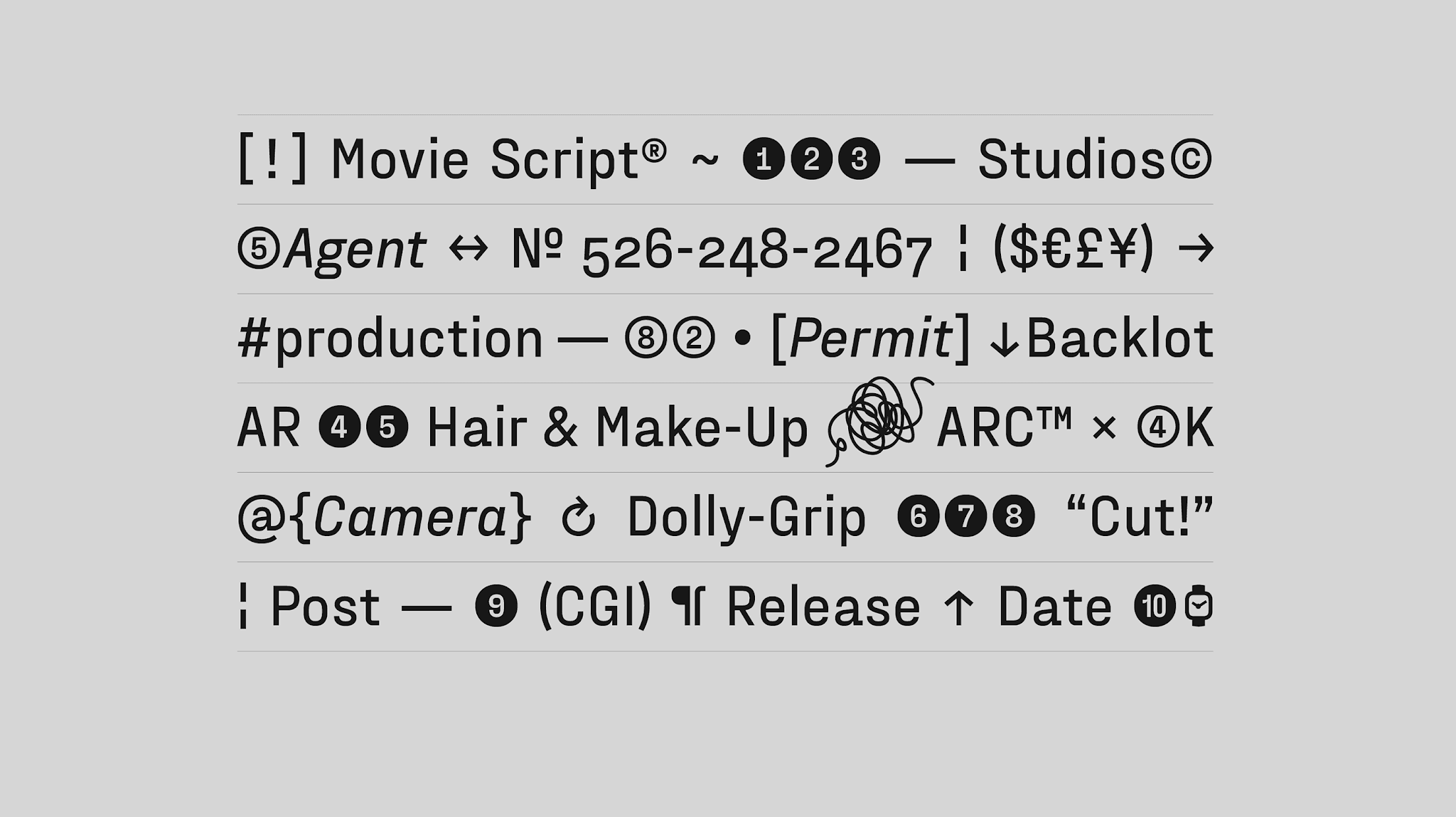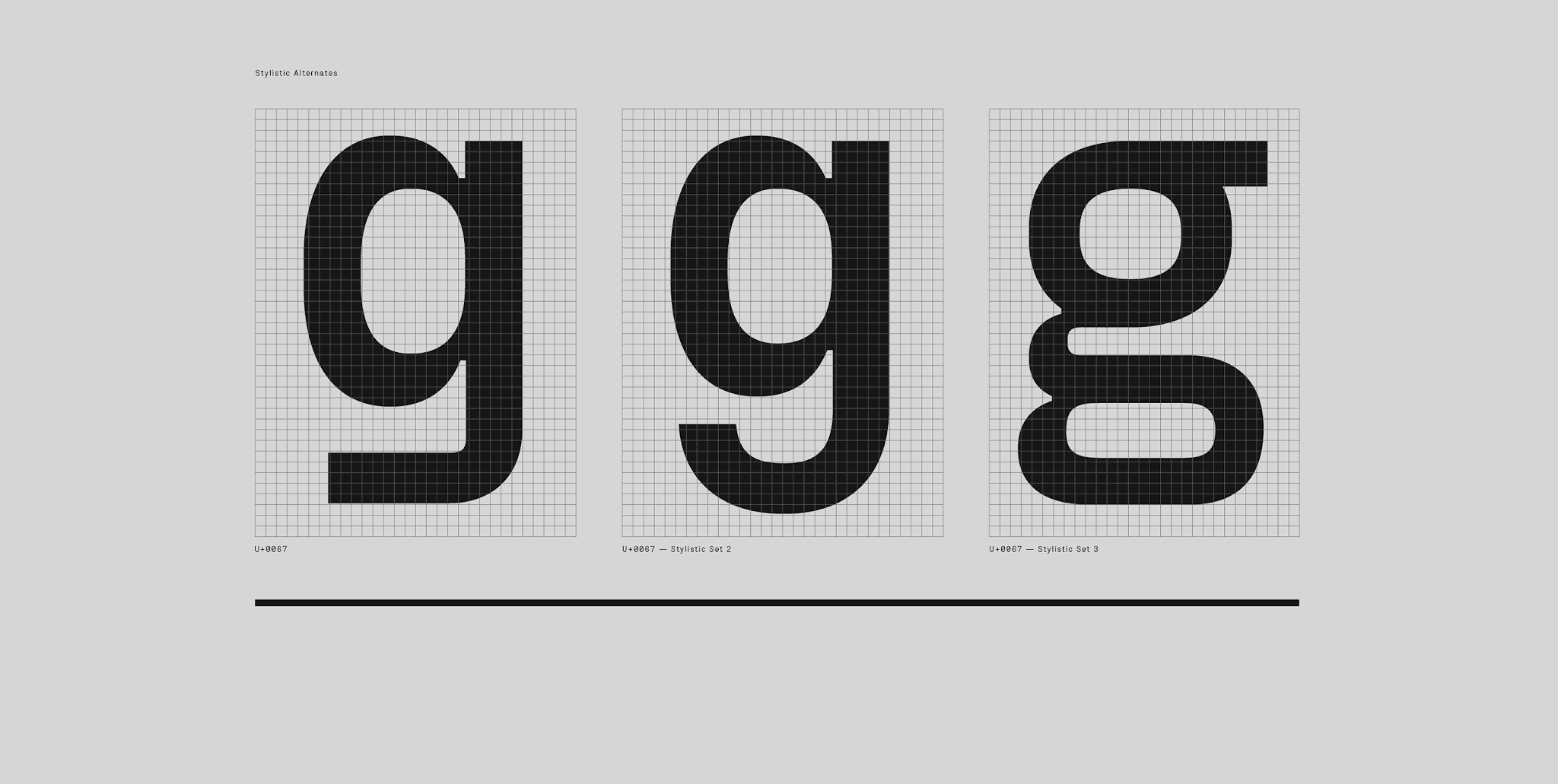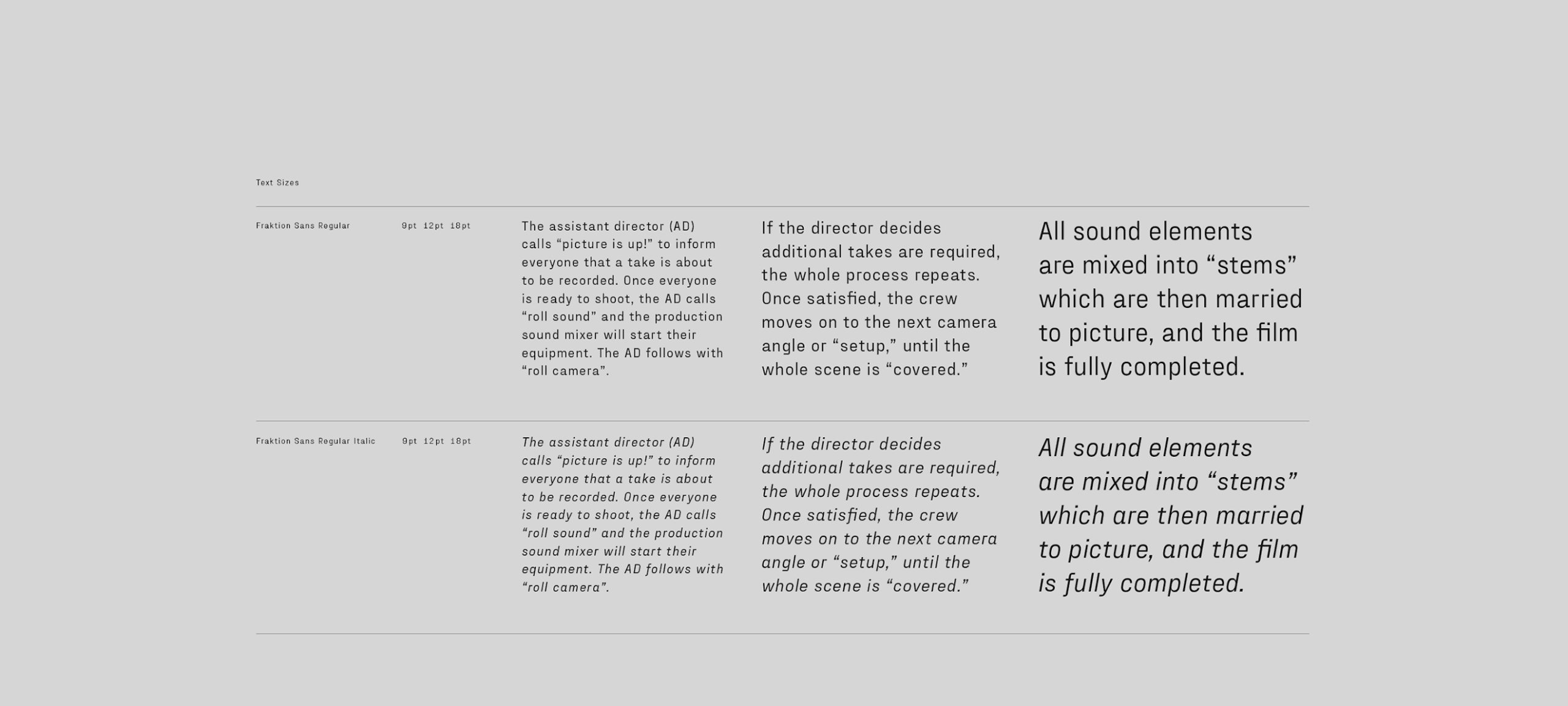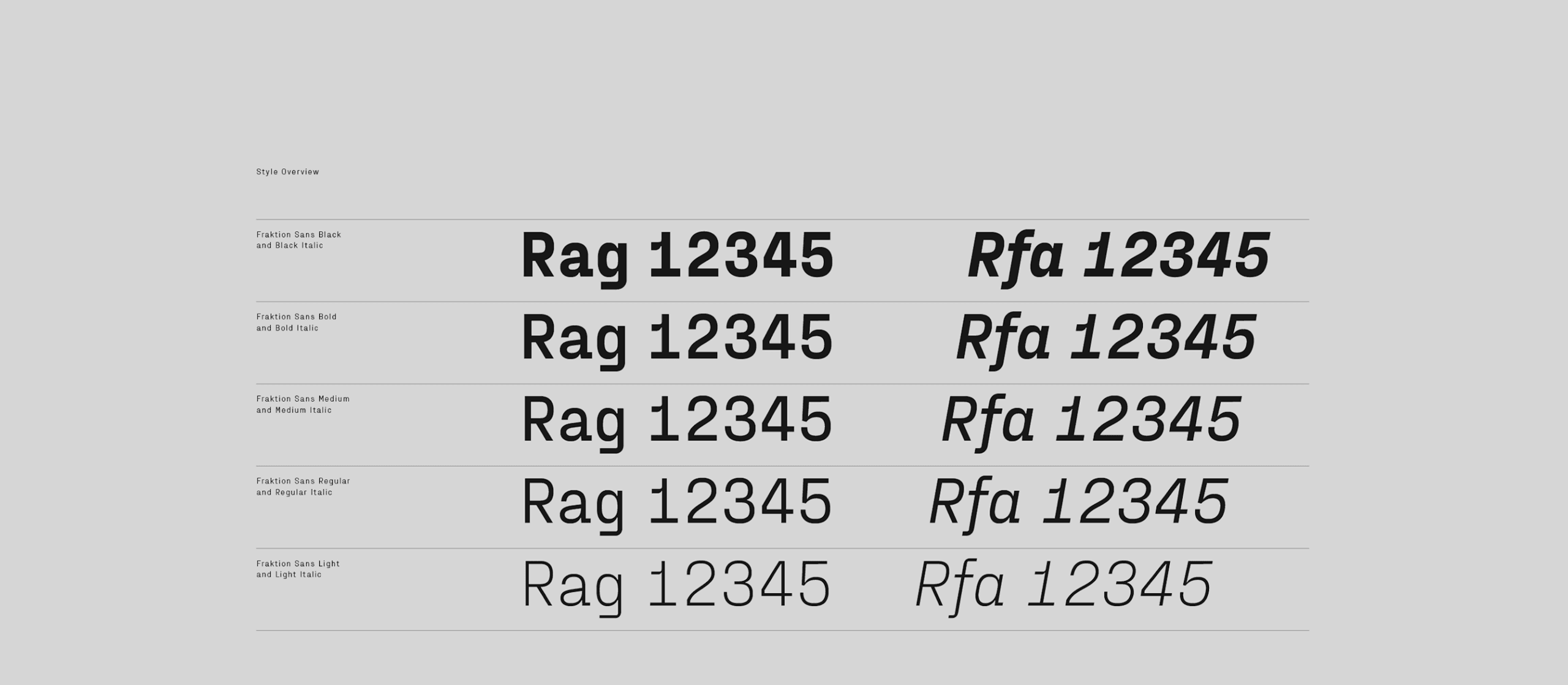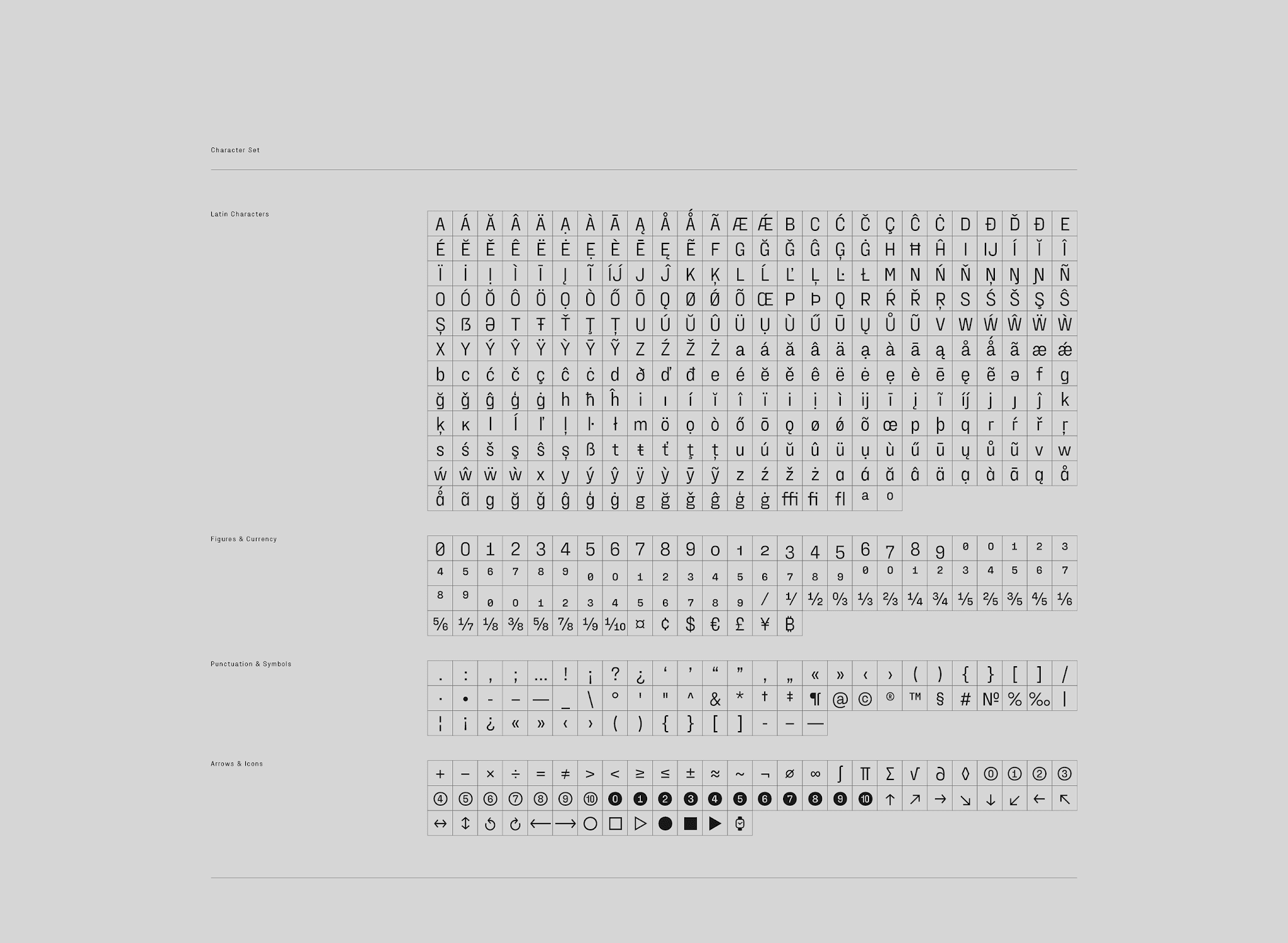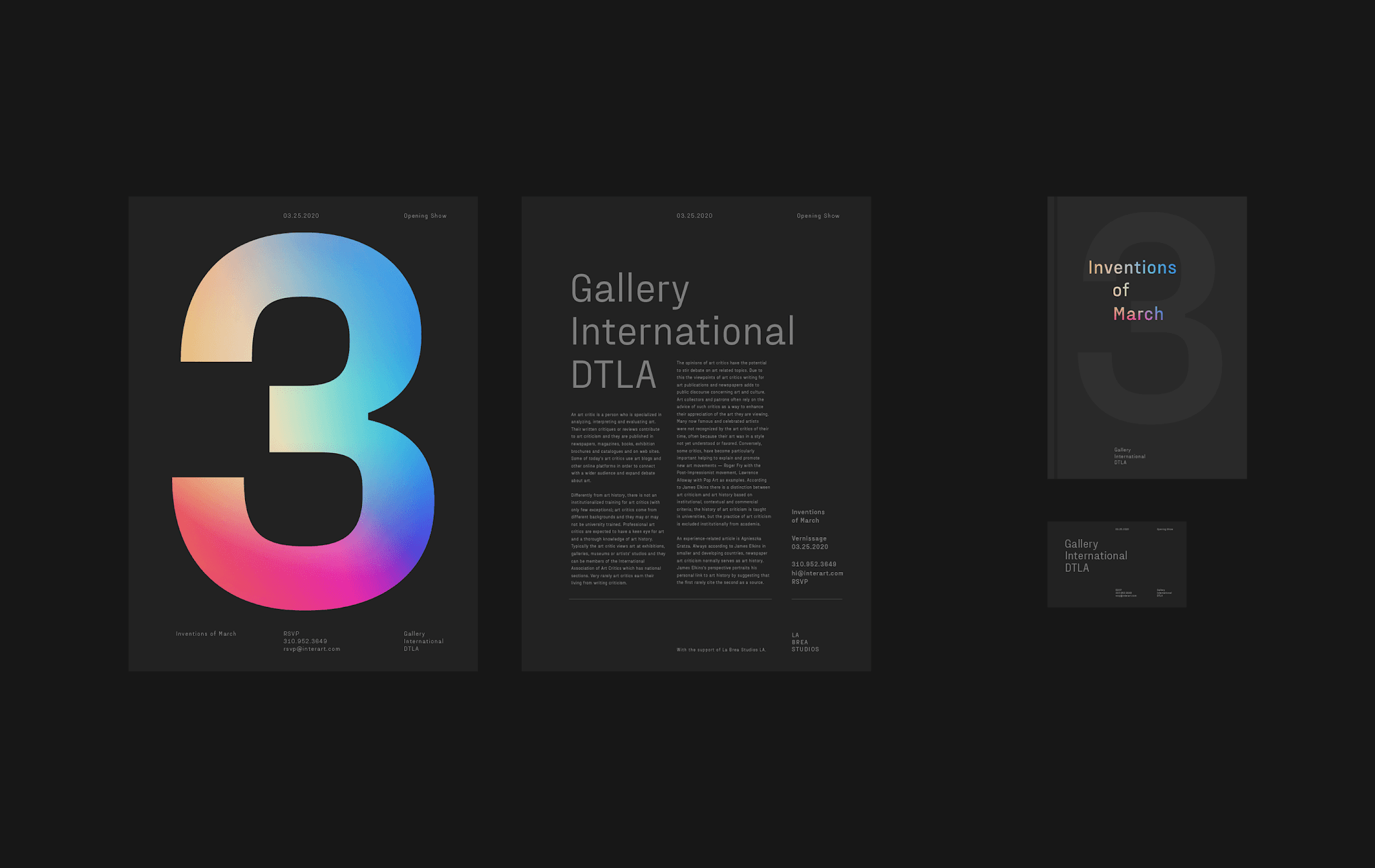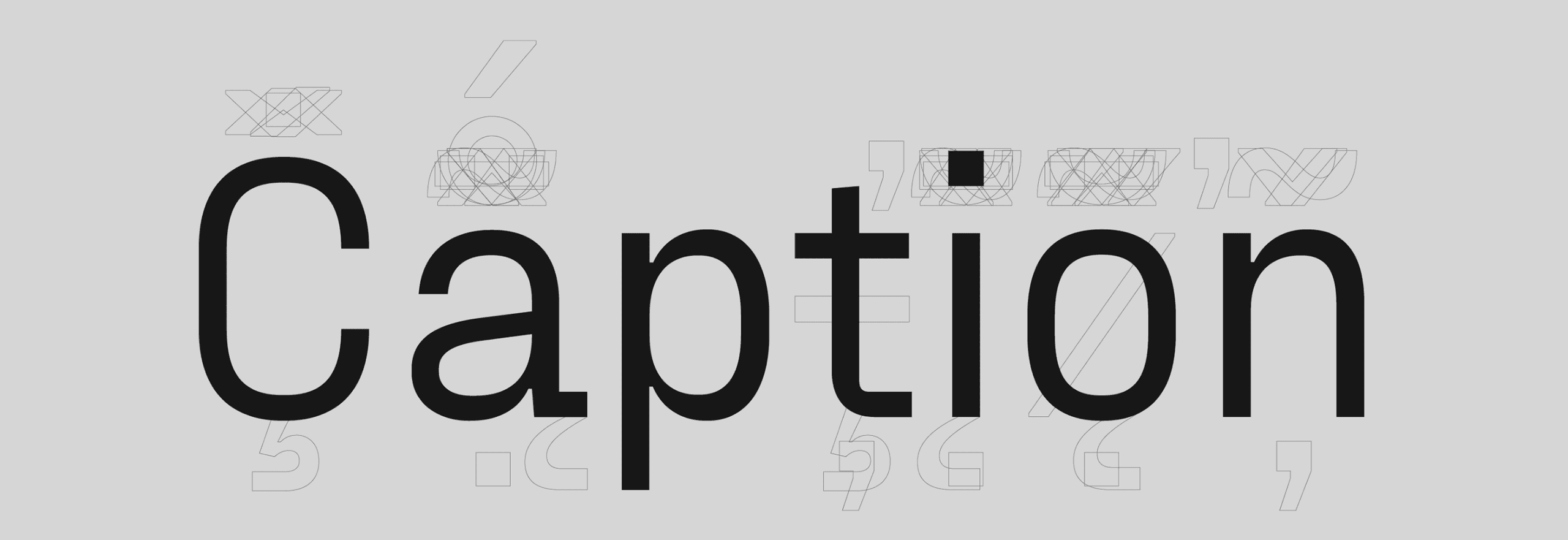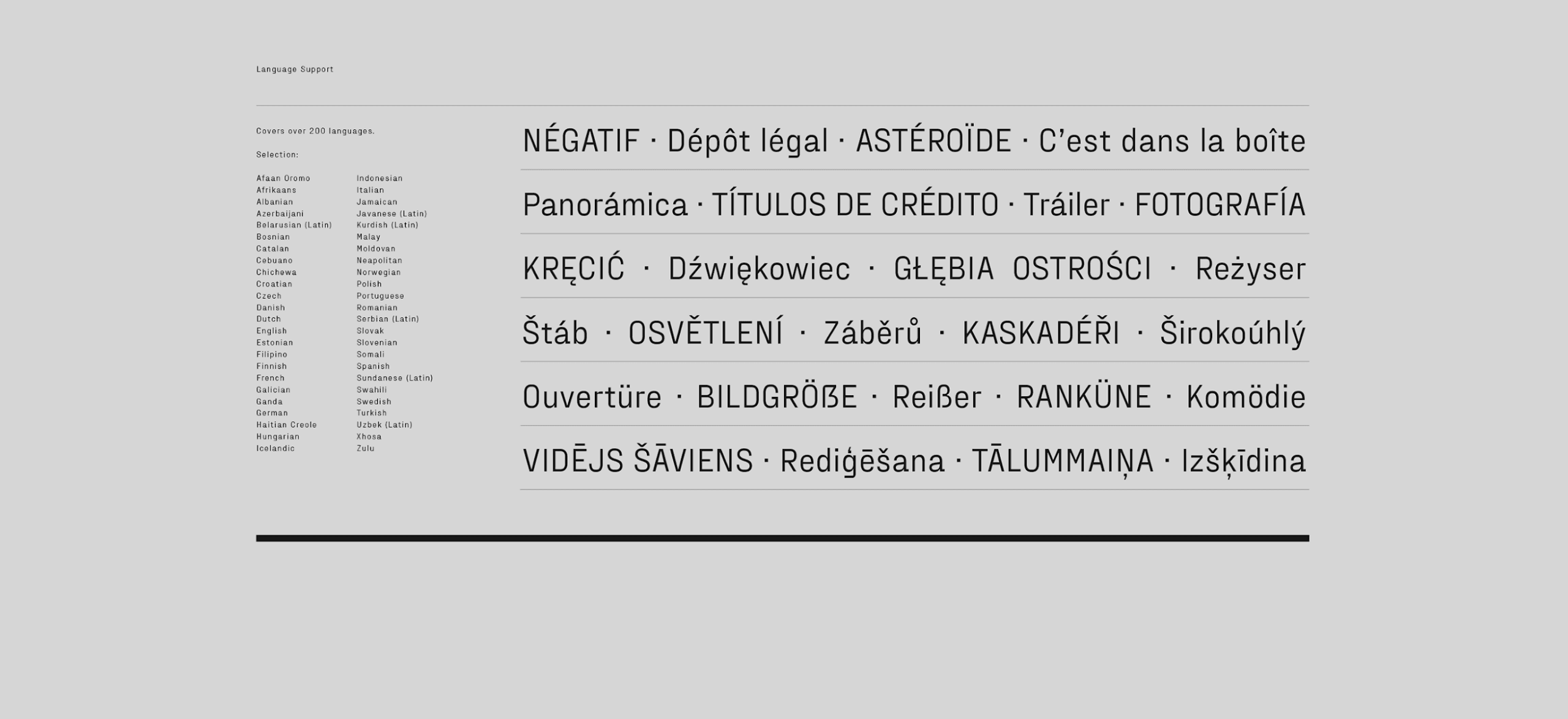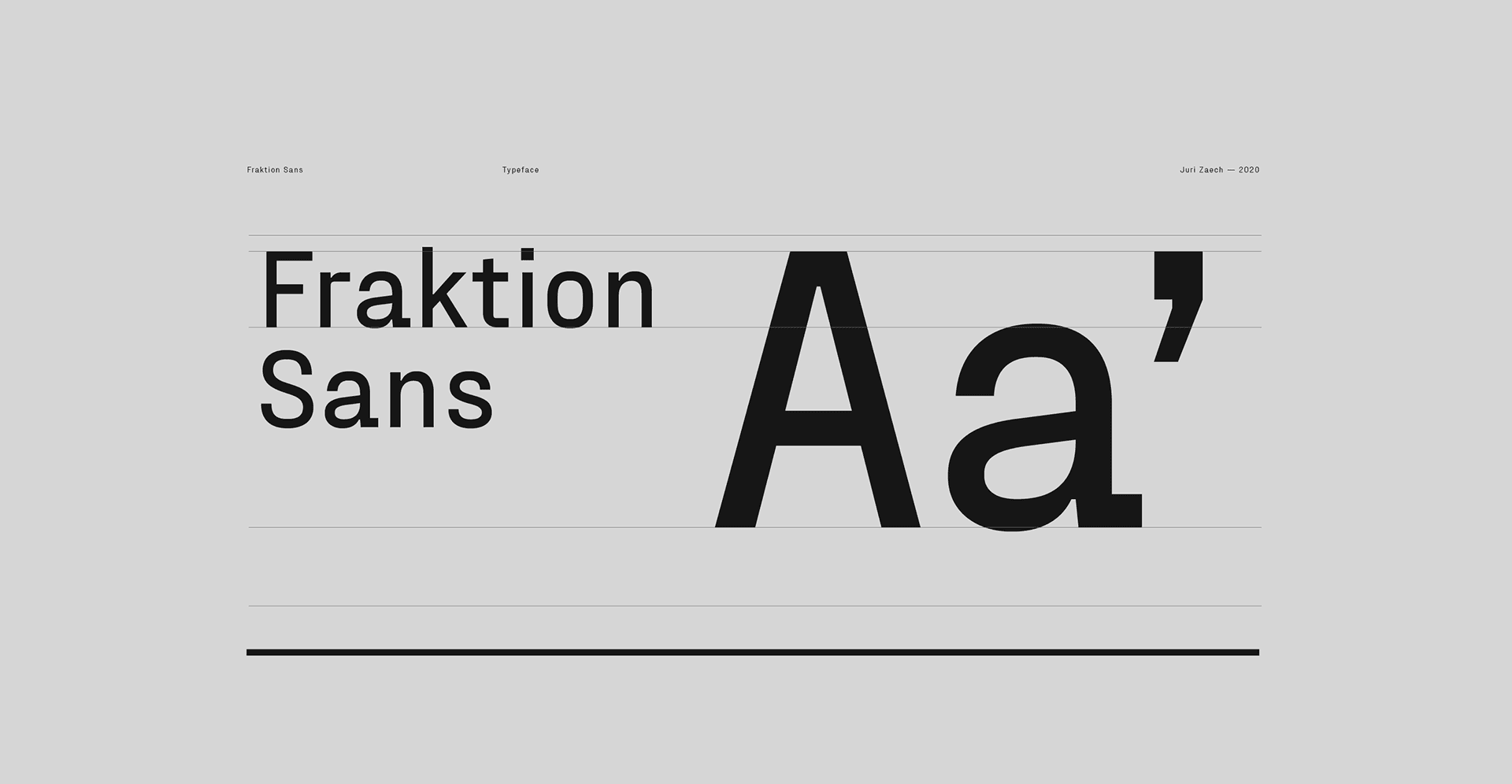
Fraktion Sans là một bộ font cực ấn tượng với thiết kế đương đại khám phá không gian giữa độ bền cơ học và sự rõ ràng của biểu cảm. Trong khi nguồn cảm hứng của nó bắt nguồn từ ký tự bảng hiệu cổ điển, thiết kế cuối cùng là một sự khởi đầu khá xa.
Hình dạng vuông vức và các chữ hoa nhỏ gọn là phần còn lại duy nhất của ảnh hưởng ban đầu và khi được thiết kế toàn bộ, sự hiện diện một cách mơ hồ. Mặc dù vậy, kiểu chữ đã được định hình thành một kiểu chữ hiện đại, linh hoạt với cảm giác nhẹ, hoạt động tuyệt vời trong bất kỳ thiết kế nào.
Bộ font bao gồm 10 kiểu với 603 glyphs mỗi kiểu. Hỗ trợ hơn 200 ngôn ngữ.